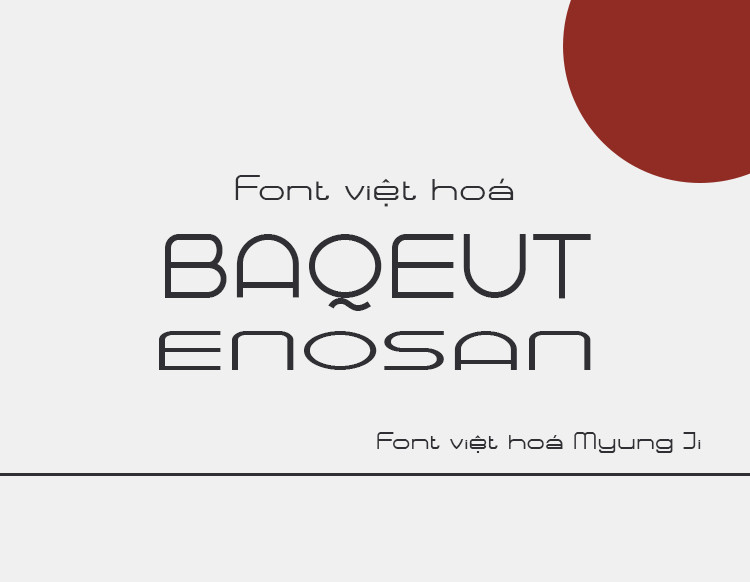
Font việt hoá MJ Baqeut Enosan
Font MJ Baqeut Enosan là một kiểu chữ độc đáo được thiết kế với mục đích tạo ra sự hài hòa giữa phong cách hiện đại và tính truyền thống trong văn hóa Việt Nam. Dưới đây là một số đặc điểm chi tiết về font chữ này:
1. Thiết kế chữ
• Kiểu dáng: Font MJ Baqeut Enosan có dạng chữ mềm mại, nhẹ nhàng, với các đường nét bo tròn, tạo cảm giác thân thiện và dễ đọc.
• Chữ cái: Các ký tự được thiết kế tỉ mỉ với độ dày và độ mảnh khác nhau, giúp tạo sự cân bằng và sinh động trong bố cục chữ viết.
2. Đặc điểm ngôn ngữ
• Hỗ trợ tiếng Việt: Font này hỗ trợ đầy đủ các dấu của tiếng Việt, bao gồm cả chữ cái có dấu như ă, â, ê, ô, ơ, ư, và các ký tự đặc biệt khác.
• Tính dễ đọc: Với thiết kế rõ ràng và tinh tế, font MJ Baqeut Enosan phù hợp cho việc sử dụng trong nhiều ngữ cảnh khác nhau, từ in ấn đến trình chiếu.
3. Ứng dụng
• Sử dụng trong thiết kế: Font này thường được sử dụng trong các sản phẩm thiết kế đồ họa, bao bì sản phẩm, và quảng cáo nhờ vào tính thẩm mỹ cao và khả năng gây ấn tượng mạnh với người xem.
• Sự kiện và truyền thông: Font cũng thích hợp cho các sự kiện văn hóa, lễ hội hoặc các chương trình truyền thông muốn truyền tải thông điệp gần gũi và thân thiện.
4. Cảm xúc và phong cách
• Cảm xúc: Font MJ Baqeut Enosan mang lại cảm giác vui tươi, năng động nhưng vẫn giữ được sự trang nhã, thích hợp cho nhiều đối tượng người dùng.
• Phong cách: Với sự kết hợp giữa hiện đại và truyền thống, font chữ này phù hợp với các thương hiệu muốn khẳng định bản sắc văn hóa của mình.
Tóm lại, MJ Baqeut Enosan là một font chữ đa năng, dễ tiếp cận với người dùng và có thể ứng dụng trong nhiều lĩnh vực khác nhau. Sự độc đáo trong thiết kế cùng với khả năng hỗ trợ tiếng Việt làm cho nó trở thành một lựa chọn tuyệt vời cho các dự án sáng tạo.